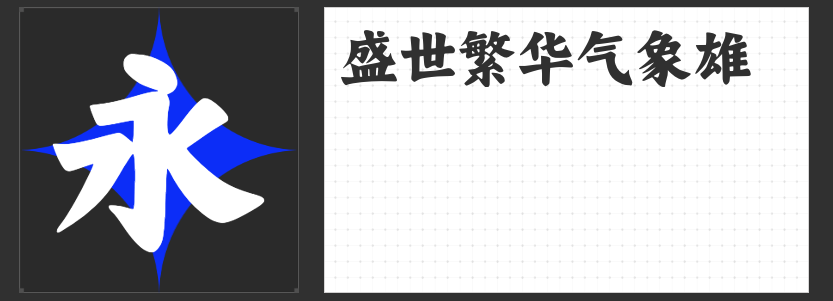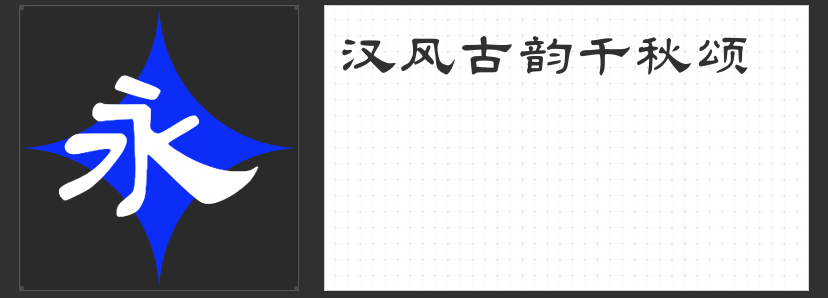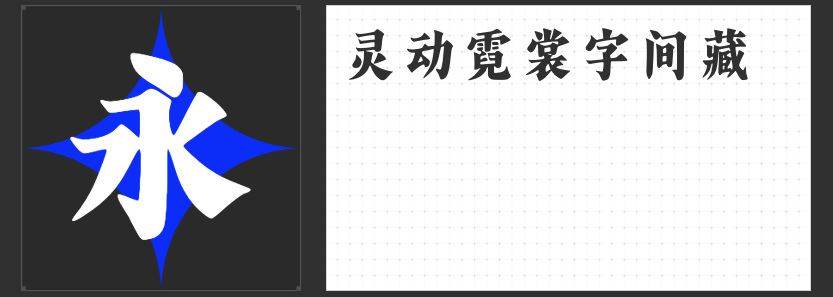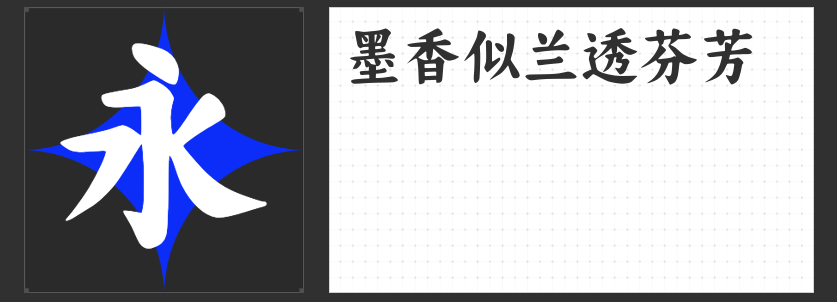
设计中的古风新韵——“小欣大萌”字体
在设计的世界里,字体不仅是文字的简单呈现,更是创意与情感的载体。今天,我要为大家推荐的是“小欣大萌”系列中的四款创意字体——“大萌唐”、“大萌宋”、“大萌汉”与“大萌明”。它们不仅各具特色,而且非常实用,能够为你的设计作品增添一抹独特的古风新韵。
1.大萌唐
这款微胖楷体以盛唐气象为灵感,字体圆润饱满,笔触间流露出大唐盛世的繁荣与自信。使用“大萌唐”字体,仿佛能让观者在字里行间感受到那份跨越千年的辉煌与魅力,非常适合用于历史题材或古风风格的设计作品。
2.大萌宋
这款温润仿宋字体,不仅承载着历史的厚重,更在现代设计的舞台上绽放异彩。其独特的温润质感,仿佛能穿越时空,将古人的风雅与现代审美巧妙融合。无论是用于书籍封面、广告设计还是品牌标识,“大萌宋”都能为你的作品增添一份古典韵味。
3.大萌汉
这款字体以古隶体为基础,加入了现代设计元素,使得大萌汉隶体更加端庄与雅致。使用“大萌汉”字体,可以让你的设计作品在保留古风韵味的同时,又不失现代感,非常适合用于书法、印章、海报等设计领域。
4.大萌明
这款字体采用明朝字体为设计参考,整体修长,笔划结构独特,同时向一个方向倾斜设计。其特点刚柔并济,有的矫健有力,仿佛刚猛的战士;有的则轻盈柔美,如同温柔的少女。这种刚与柔的交织,使得“大萌明”字体独具魅力,令人陶醉。无论是用于标题设计、正文排版还是品牌宣传,“大萌明”都能为你的作品增添一份独特的视觉美感。
总的来说,“小欣大萌”系列字体以其独特的古风韵味和实用性,成为了设计领域中的一颗璀璨明珠。无论你是从事平面设计、UI设计还是品牌策划,都能在这些字体中找到适合自己作品风格的那一款。快来尝试吧,相信你会有不一样的收获!